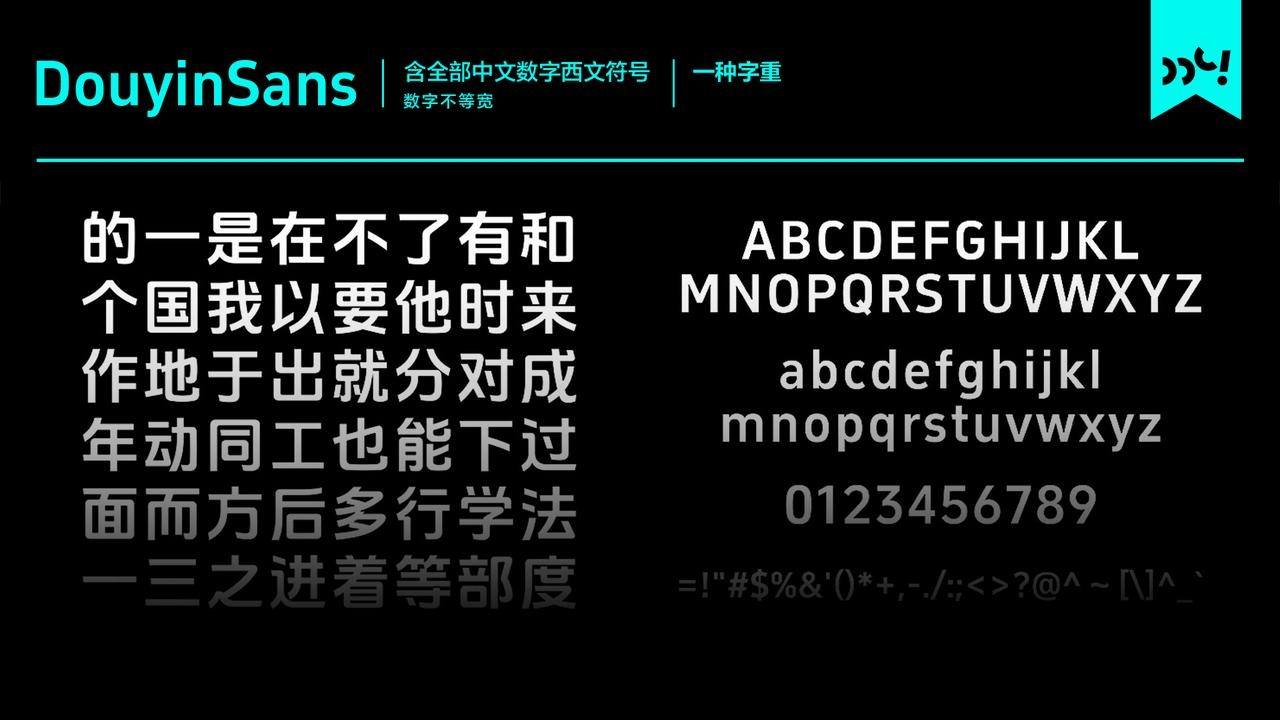
抖音美好体 字节跳动 字体信息 字体类型 黑体 无衬线 字体语言 简体中文 英文 字体名称 抖音美好体 字体PostScript名称 DOUYINSANS 字体字符集 简/英 字体字重数量 1 #中文字体 #黑体 #OFL 开源协议 #免费商用字体 #免费字体下载 #抖音美好体 #排版 免费 原创 原创 · 免费可商用 支持作者 查看下载选项 授权地址 https://github.com/bytedance/fonts 许可协议 SIL Open Font License 1.1 原创 · 免费可商用 海报 包装 出版物 转售品 互联网 视频 文稿 商标 嵌入 衍生 许可范围仅供参考,不代表法律建议,请以字体品牌方声明为准。 快速预览 粗体 字重 字重预览 0个字重 “抖音美好体”由抖音品牌创意中心研发并发布,作为平台的专属官方字体,不仅具备完整的自主知识产权,也大方地对外开放了授权。字库内共收录了6763个汉字以及682个数字与西文符号,基本能覆盖日常的图文排版与视频字幕需求。整体笔画设计走简洁凝练的路线,字形饱满舒展,刚柔线条穿插得当,视觉呈现厚重又挺拔。放在屏幕上阅读非常顺畅,长时间观看也不会觉得累。它的推出既是为了贴合抖音“记录美好生活”的产品理念,也是为了让创作者在编辑内容时有更趁手的文字工具。目前已经免费开放,欢迎大家尽情取用! License SIL Open Font License 1.1 字节跳动 这个人很懒,什么都没写... 关注 私信 发布于 2026-08-26T06:58:59Z 相关作品 Fredoka 75 Cairo 48 Red Hat Display 51 Josefin Sans 48 Noto Sans Telugu 57 Rounded Mplus 1c 54